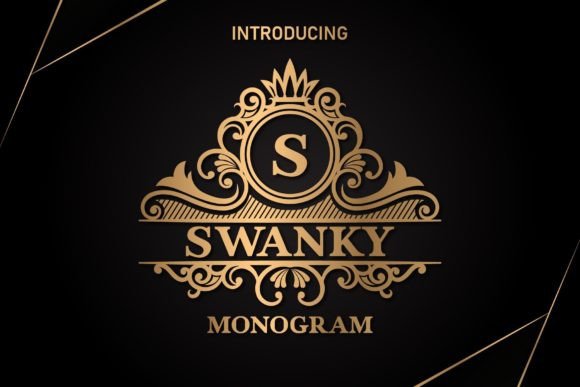
Swanky Monogram
Swanky Monogram – A Fonte Vintage que Transforma Seu Design
Se você procura uma fonte que una elegância vintage e sofisticação contemporânea, Swanky Monogram é a escolha perfeita. Esta fonte monograma luxuosa vem acompanhada de fontes serif compatíveis, proporcionando um conjunto tipográfico completo para projetos de alto padrão.
Por que escolher Swanky Monogram?
- Estilo Vintage Autêntico: Cada caractere foi desenhado à mão, garantindo um visual clássico que remete à era dourada das tipografias elegantes.
- Versatilidade Criativa: Ideal para convites de casamento, papelaria de luxo, postagens chamativas nas redes sociais e cartões de felicitações.
- Compatibilidade de Fontes: O pacote inclui fontes serifas que combinam perfeitamente, facilitando a criação de hierarquias tipográficas harmoniosas.
- Impacto Visual: Adicionar Swanky Monogram a qualquer projeto eleva instantaneamente a percepção de qualidade e exclusividade.
Como Swanky Monogram pode melhorar seus projetos
Ao incorporar Swanky Monogram em suas criações, você percebe rapidamente a diferença: os textos ganham presença, os detalhes se destacam e a identidade visual se torna memorável. Seja para:
- Convites de casamento luxuosos
- Cartões de agradecimento personalizados
- Postagens de Instagram que atraem curtidas
- Materiais de branding premium
- Design de embalagens sofisticadas
Conclusão – Dê vida às suas ideias com Swanky Monogram